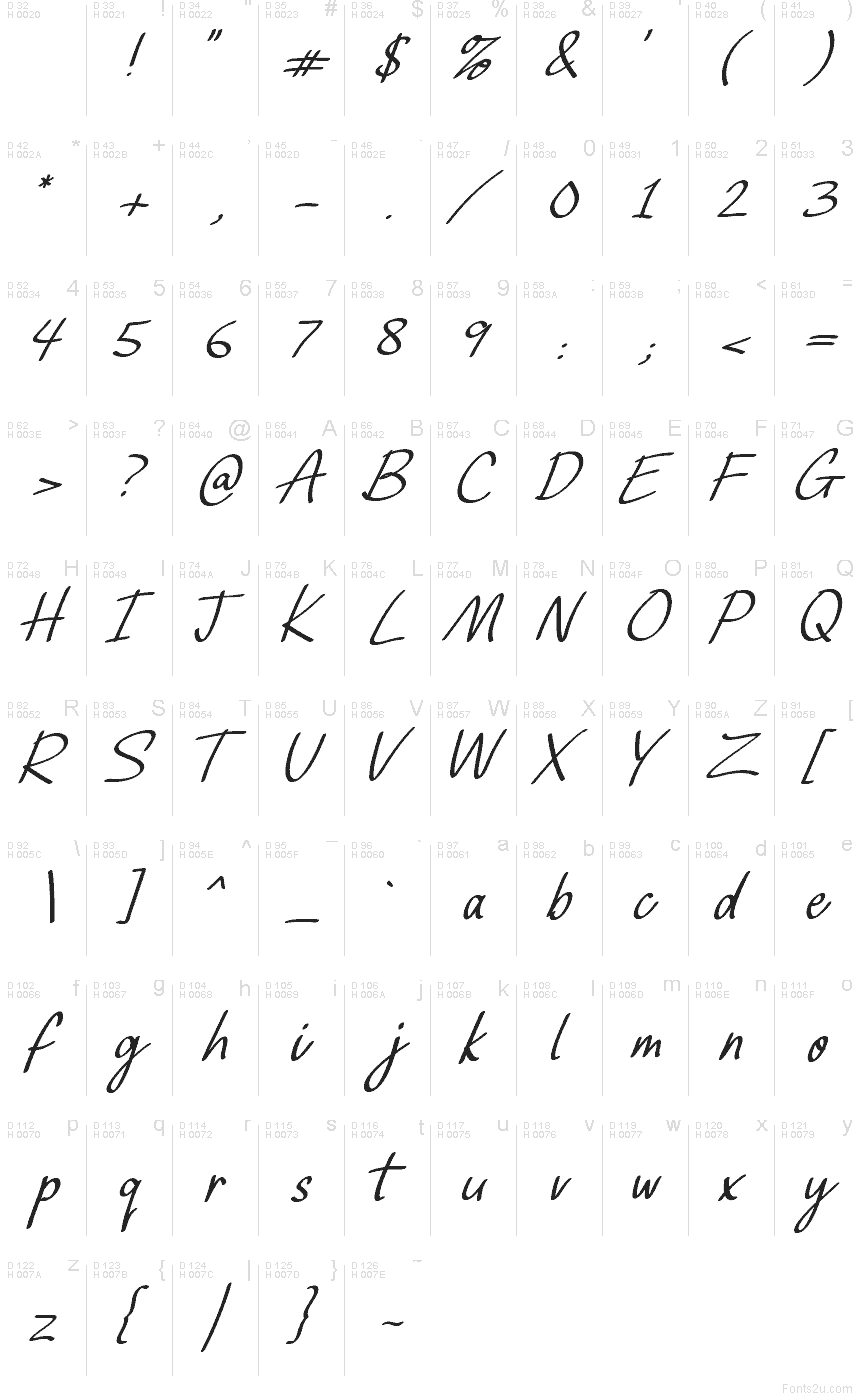
Everista von Rinaldo Hasibuan ist eine kostenlose, handgeschriebene Skript-Schrift mit einem lockeren, luftigen Rhythmus, der an eine schnelle Unterschrift erinnert. Die Buchstaben bestechen durch lange, geschwungene Striche und weiche Verbindungen, während die hohen Versalien der Schrift eine modische, persönliche Note verleihen.
Sie passt perfekt zu Branding, Boutique-Verpackungen, Social-Media-Headern, Einladungskarten und Magazin-Covern, bei denen es auf einen spontanen statt zu formellen Look ankommt. Setzen Sie die Schrift für kurze Sätze, Namensschilder oder Titelkarten ein – die ausgeprägten An- und Abstriche verleihen selbst kurzen Textzeilen Dynamik und Präsenz.